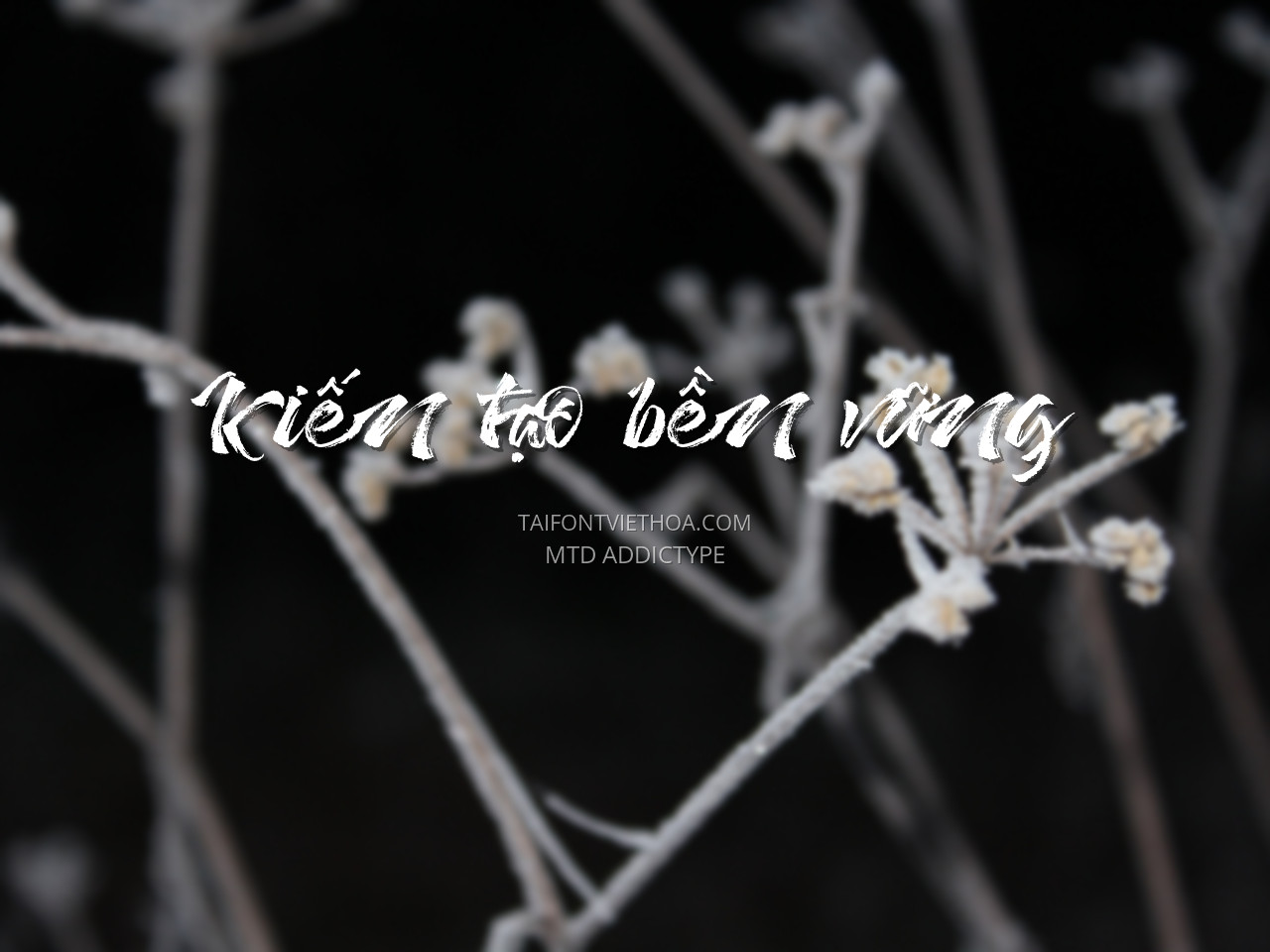
Font việt hóa MTD Addictype
Giới thiệu về font Addictype – Phong cách script đầy quyến rũ và hiện đại
Addictype là một kiểu font script hiện đại được thiết kế với các đường nét cong mượt, uyển chuyển và tinh tế như được viết bằng tay một cách điêu luyện. Font mang trong mình sự quyến rũ pha chút táo bạo, lý tưởng để thể hiện cảm xúc mạnh mẽ, cá tính và thời thượng trong các thiết kế thương hiệu hoặc cá nhân hóa cao. Font này thường được ưa chuộng trong các sản phẩm mang tính nghệ thuật, thời trang hoặc truyền cảm hứng.
Phiên bản Việt hóa do Mộc Hạthực hiện đã hỗ trợ đầy đủ tiếng Việt, đồng thời giữ nguyên tinh thần phóng khoáng của bản gốc. Taifontviethoa.comđã chọn lọc và giới thiệu Addictype như một công cụ đắc lực dành cho những nhà thiết kế đang tìm kiếm một kiểu chữ mềm mại nhưng vẫn đậm chất cá tính và hiện đại để tạo dấu ấn khác biệt trong thiết kế bằng tiếng Việt.
Đặc điểm thiết kế mềm mại và ứng dụng nổi bật của font Addictype
Addictype sở hữu các đường cong uốn lượn, kết nối linh hoạt giữa các ký tự, tạo cảm giác liền mạch và duyên dáng. Với trọng số chữ không quá nặng, font duy trì sự cân bằng giữa nét nữ tính và phong cách thời trang hiện đại. Các ligatures và alternate đi kèm giúp mở rộng khả năng biểu cảm, đặc biệt trong logo hoặc thiết kế cá nhân.
Font phù hợp cho các ứng dụng như: logo thương hiệu thời trang nữ, tiêu đề blog, bao bì mỹ phẩm, thiệp cưới, trích dẫn nghệ thuật hoặc bài đăng mạng xã hội mang tính cảm xúc. Ngành nghề lý tưởng: thời trang, làm đẹp, cưới hỏi, thiết kế sáng tạo, lifestyle và các thương hiệu hướng đến sự nữ tính, sang trọng và mang dấu ấn cá nhân cao.